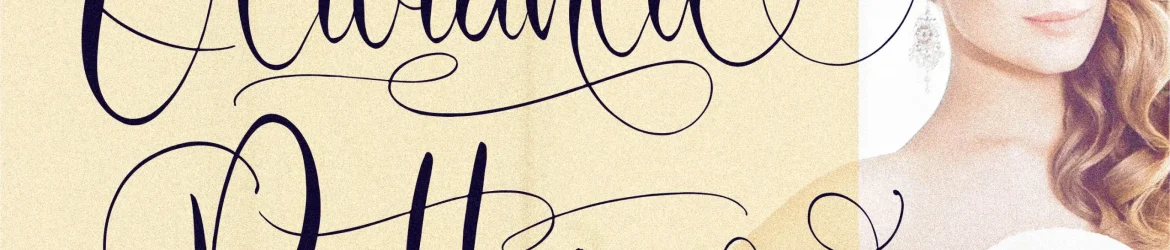
Olivianta Pettcia Font – Download Grátis
A olivianta Pettcia é uma elegante tipografia romântica perfeitamente adaptada para uma variedade impressionante de projetos. Suave e charmosa, esta fonte calligráfica se encaixa perfeitamente em trabalhos como identidades de marca, designs de mobiliário, embalagens de produtos, e até mesmo em materiais que são carregados com um toque especial, como camisas personalizadas, sacolas de shopping ou cartões promocionais. Perfeita para letras de convites, cartas de agradecimento e até cartazes publicitários. Com sua graça única, a olivianta Pettcia é uma escolha perfeita não apenas para aqueles que procuram um toque delicado em suas criações, mas também para quem busca uma expressão sofisticada em qualquer projeto. Este é um excelente adorno para textos informativos e até mesmo para marcas de água em fotografias especiais ou para aniversários únicos. Seja no seu próximo design de identidade de marca, embalagem de produto personalizada, ou até mesmo em cartões de presentes, a olivianta Pettcia será uma escolha perfeita para tornar seus projetos ainda mais amáveis e belamente escritos.